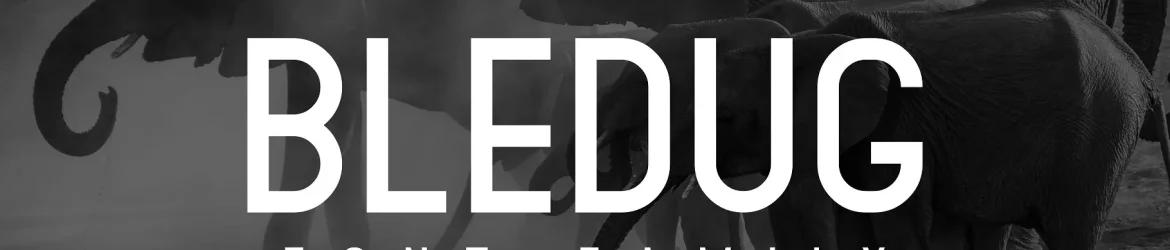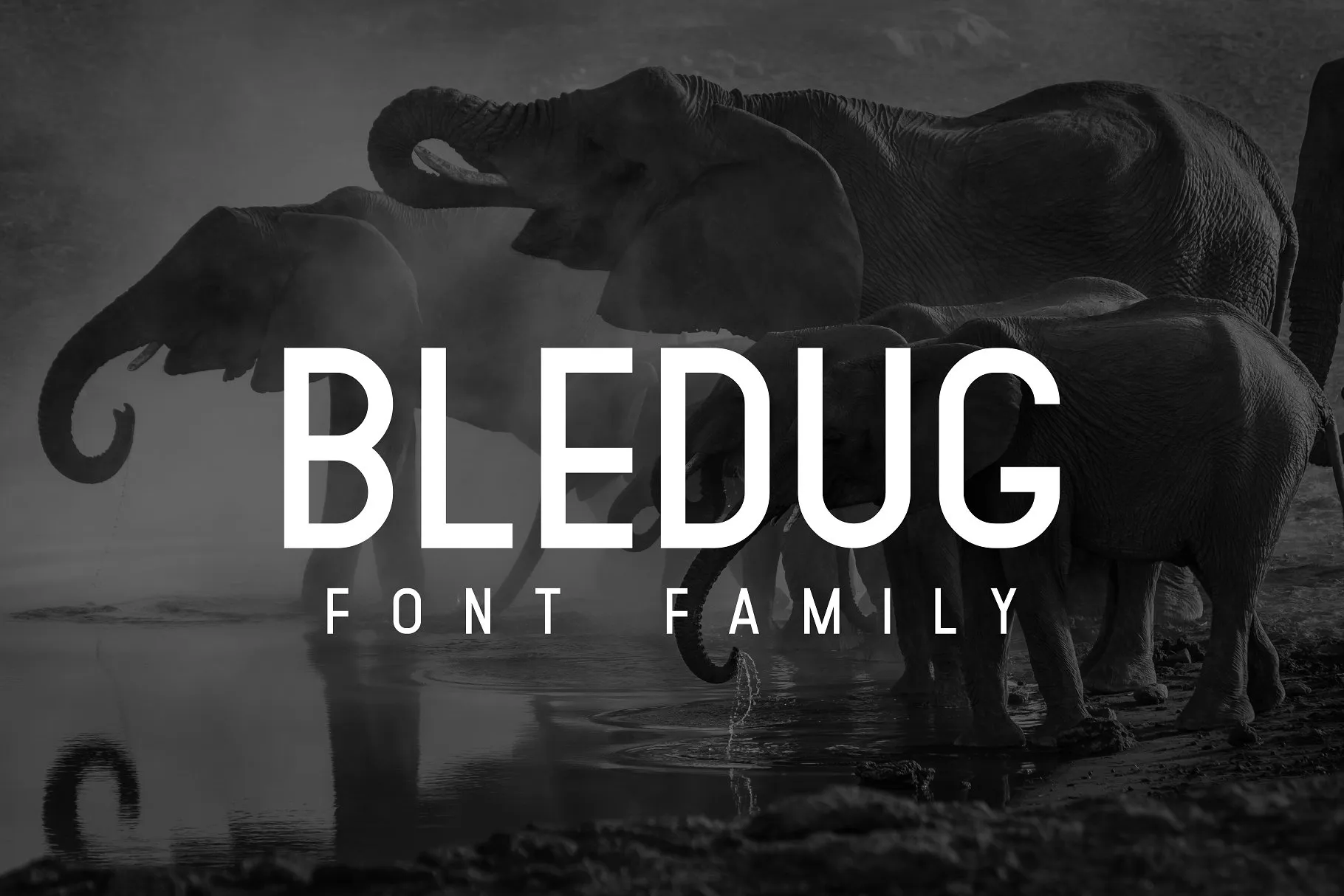
Bledug Font Family – Fonte Grátis
Bledug Font Family
Bledug Font Family é uma tipografia moderna e versátil, projetada para oferecer uma aparência clara e sofisticada. Esta família sans-serif vem em 8 estilos diferentes, com três pesos (light, regular e bold), três itálicos, um traço sobreposta e até mesmo linhas pontiagudas. Suas características clean e minimalistas a tornam ideal para uso nas seções de destaque, identidades visuais de marcas, outdoors e logotipos. É uma fonte que encaixa perfeitamente em revistas e publicações de jornais, oferecendo um acabamento profissional em qualquer aplicação visual. Com seu design clean e elegante, a Bledug é certamente uma opção ótima para designers buscando criar ambientes visuais modernos e contemporâneos.